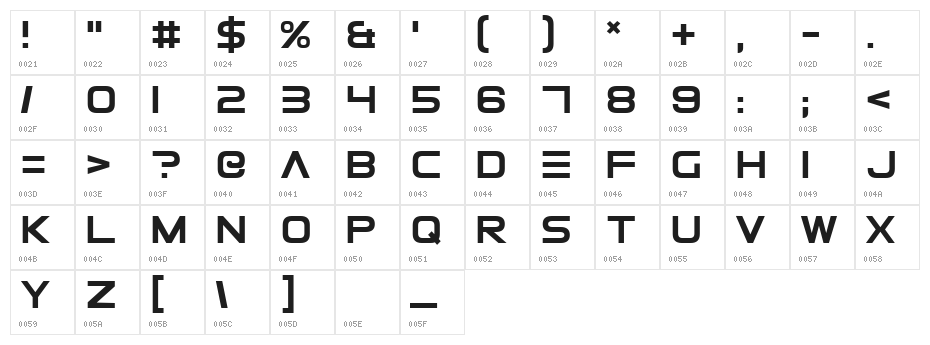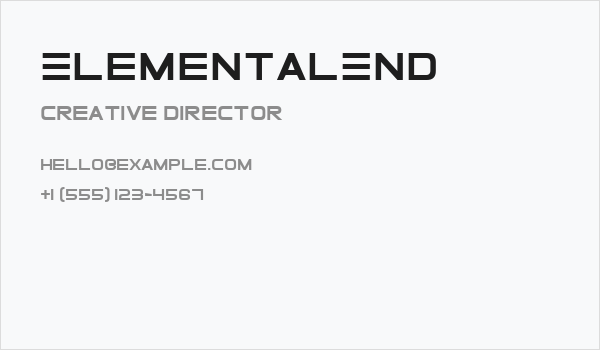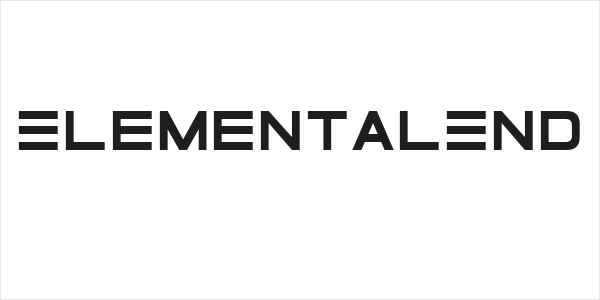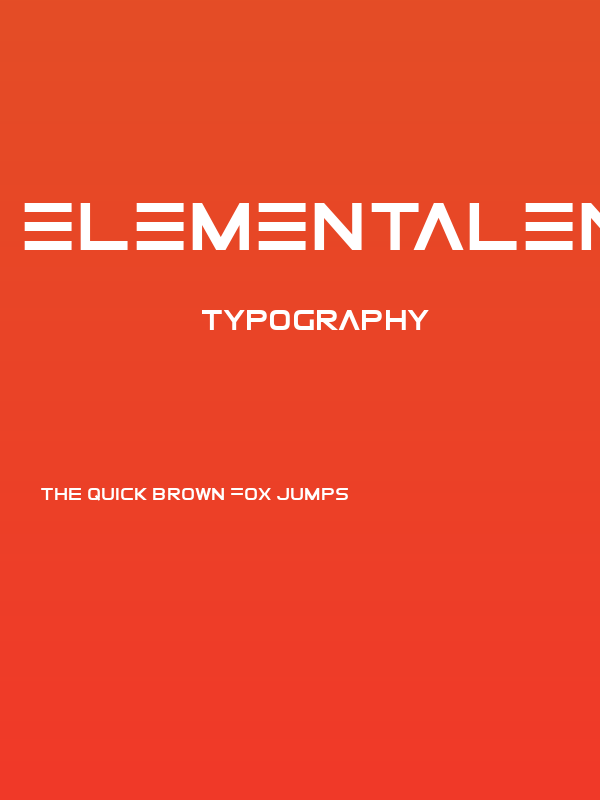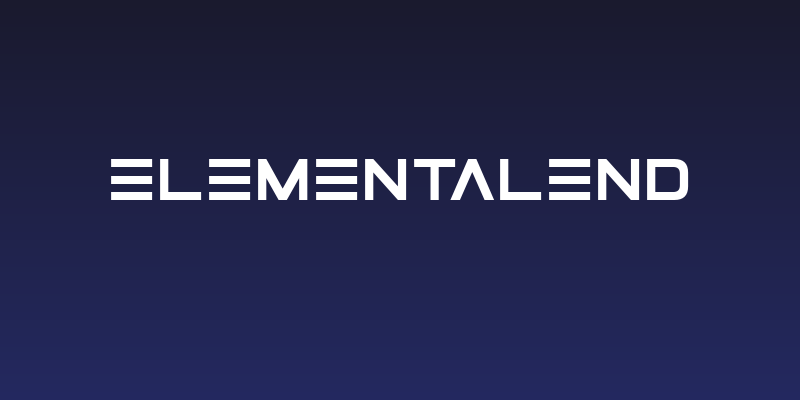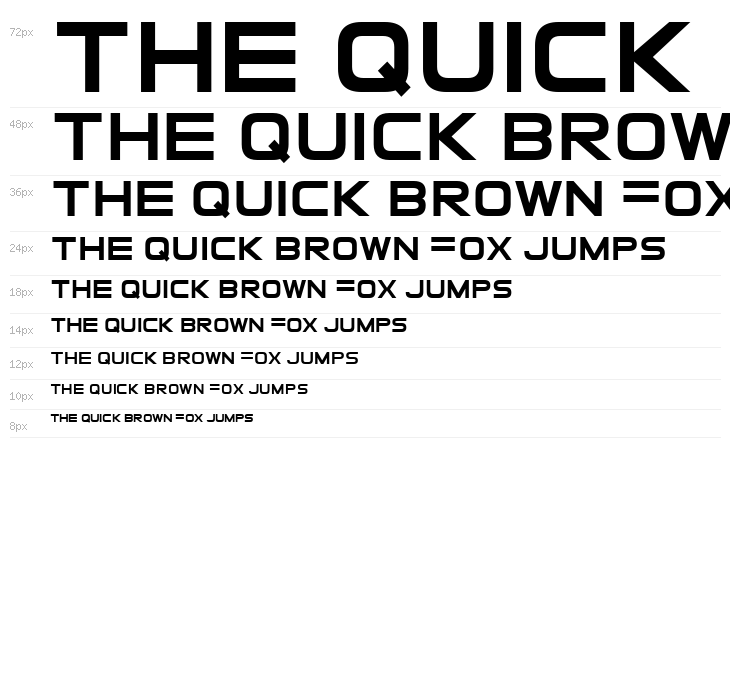
ElementalEnd Font
| 分类 | Futuristic |
| 使用场景 | Headlines, Logos, Digital Interfaces |
| 推荐项目 | Ideal for technology branding, modern advertising, digital interfaces, and futuristic-themed designs. |